たづがね角ゴシック:鉄道分野のデジタルサイン表示
東海旅客鉄道株式会社(JR東海)は、東京、名古屋、大阪間を結ぶ日本の交通の大動脈で、東海道新幹線をはじめ東海エリア在来線を運営しており、日本国有鉄道が1987年に分割民営化した際の 旅客鉄道会社の一社です。
JR東海は、かつて国鉄であった時代に開発された独自書体で「すみ丸角ゴシック体」を使っていました。「明朝体」や「ゴシック体」のような選択肢 しかなかった時代に、柔らかで調和のとれたデザインの「すみ丸角ゴシック体」は、駅名標や方向幕などに広く普及し長きにわたり親しまれてきました。 かつての反転フラップ式から移行したデジタル表示であるLED(Light Emitting Diode)式運行表示器になってからは、列車名や停車駅、時刻表示などにはゴシック体が使用され、旅行者への案内情報などは明朝体で表示されていました。
LCD式運行表示器(東京駅)
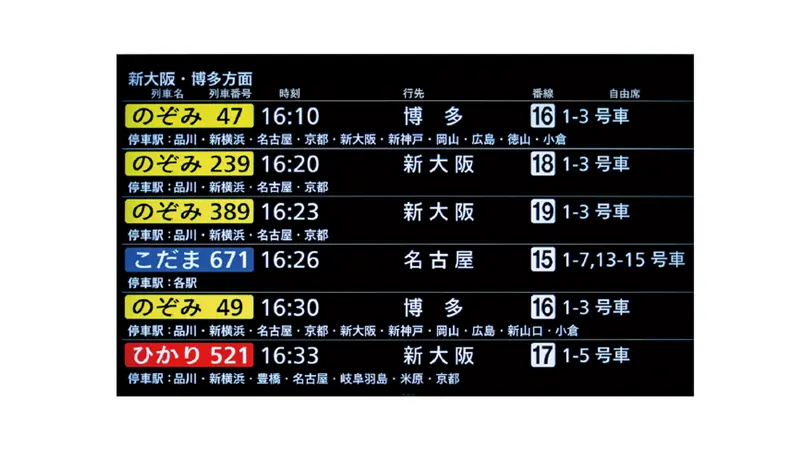
LCD式運行表示器(新大阪駅)
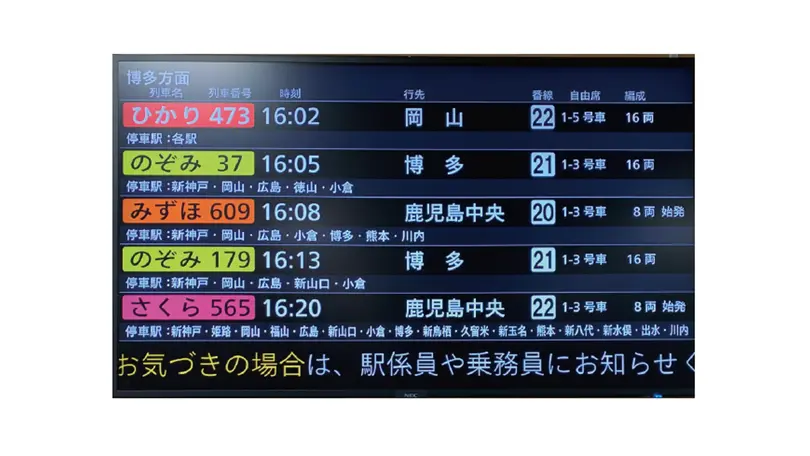
さらに、JR 東海がこれまでに培ってきた歴史的、 文化的背景を新しい世代や環境へ繋いでいくために、「すみ丸角ゴシック体」を基調として組まれた列車名(のぞみ、ひかり、こだま、さくら、みずほ)の中から特徴を抽出し、たづがね角ゴシックのデザインに反映させたカスタム書体を提供しました。 2020年度導入予定のN700S新型車両のLCD 式車内テロップ(列車案内情報装置)にも同様のたづがね角ゴシックが選定されました。また、英語話者に対しても簡明に情報が伝えられるよう、Neue Frutiger のコンデンス体も採用されています。これらの書体によって、JR 東海はより快適な環境を提供することを目指しています。
たづがね角ゴシックの標準字形をカスタム
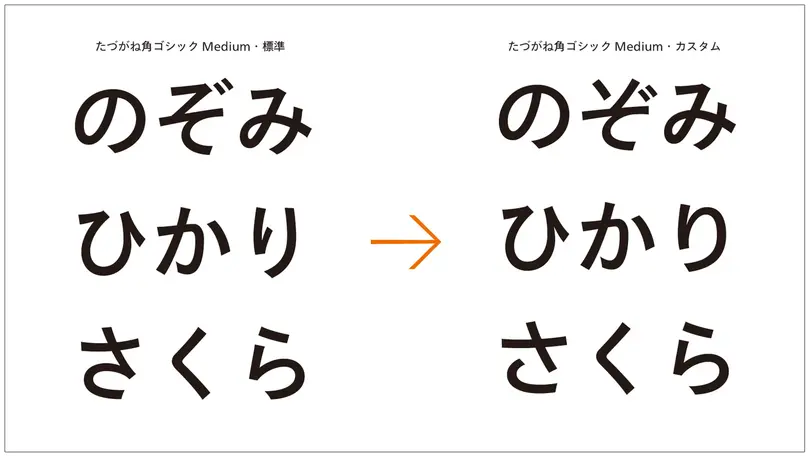
LCD式車内テロップ